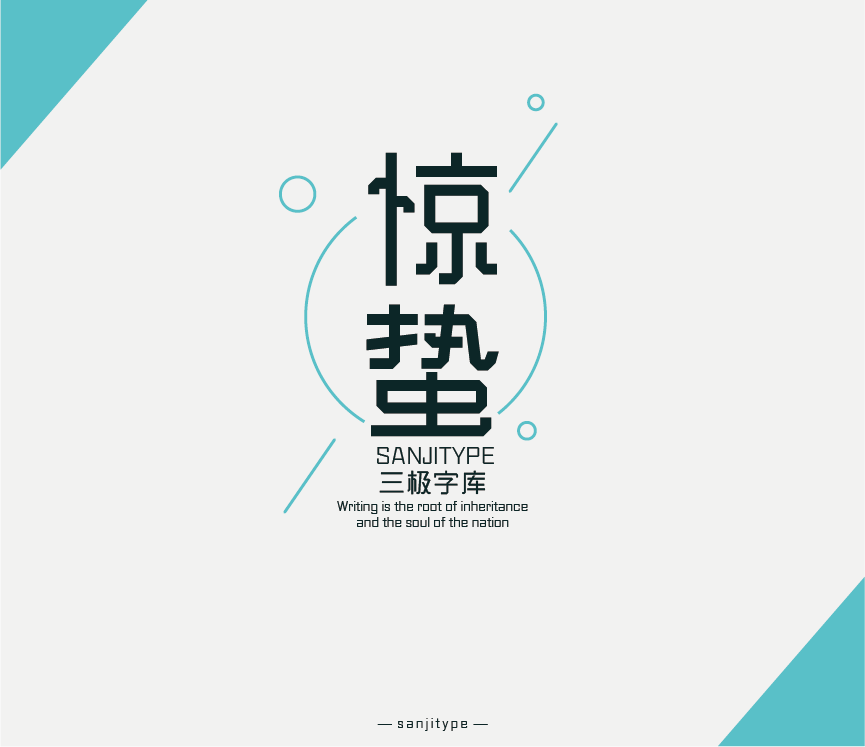
三极折纸体简-粗
字体名称:
三极折纸体简-粗
设计师:
何逸惠,曹陆迎
所属分类:
创意字体
字体简介
三极折纸体简是一款匠心独具的字体,笔画线条粗细均匀,且笔画均做了折角变化的处理。惊蛰时节,春雷始鸣,惊醒蛰伏于地下越冬的蛰虫。字体笔画的折角设计使字体整体看起来如蛰虫般,象征着春气萌动,万物复苏,大自然有了新的活力。
适用媒介:杂志、书籍、广告、标志、宣传册、包装、影视、动漫、交互设计。